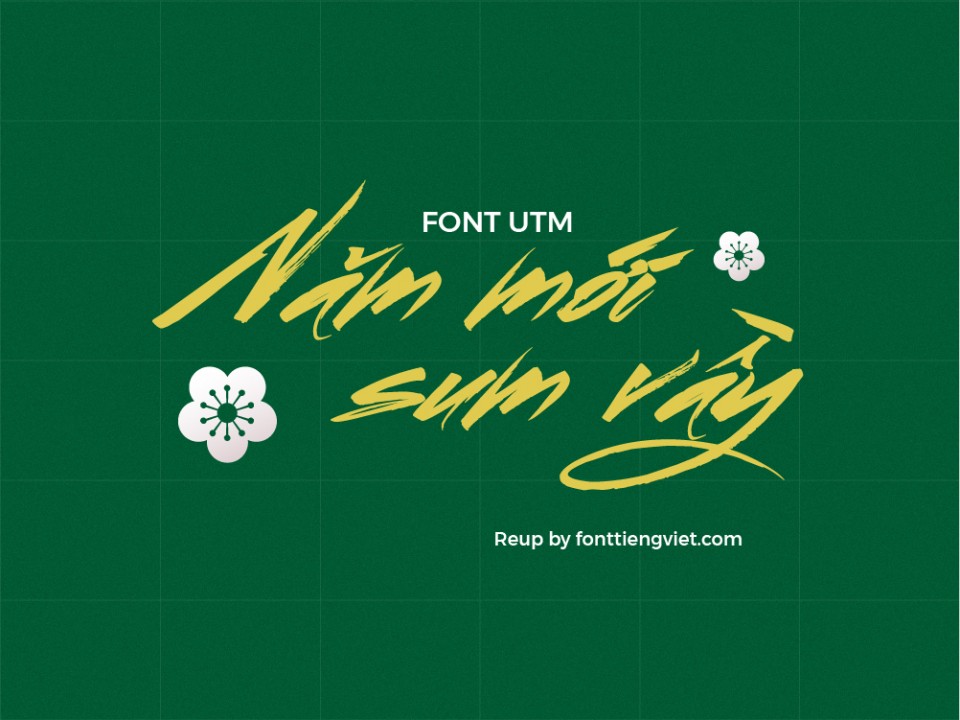
Giới thiệu về Font việt hóa UTM Ông Đồ Trẻ – Tết
Trong không khí rộn ràng của những ngày cuối năm, việc tìm kiếm một bộ Font Chữ mang đậm bản sắc văn hóa dân tộc là điều vô cùng cần thiết. Font việt hóa UTM Ông Đồ Trẻ – Tết chính là lựa chọn hoàn hảo để thổi hồn vào các thiết kế chúc mừng năm mới. Được phát triển dựa trên phong cách thư pháp hiện đại, bộ font này không chỉ giữ được nét mềm mại, uyển chuyển của bút nghiên mà còn mang hơi thở trẻ trung, năng động. Đây là công cụ đắc lực giúp các bạn học sinh và thầy cô dễ dàng tạo ra những tấm thiệp, biểu ngữ hay báo tường đầy ấn tượng cho dịp Tết nguyên đán sắp tới.
Đặc điểm nổi bật của bộ font thư pháp hiện đại
Thiết kế tối ưu cho tiếng Việt
Điểm mạnh nhất của Font việt hóa UTM Ông Đồ Trẻ – Tết là khả năng hiển thị tiếng Việt hoàn hảo, không bị lỗi dấu hay sai lệch khoảng cách. Từng nét chữ được chăm chút tỉ mỉ, mô phỏng lại cách đưa bút của những ông đồ thời nay, vừa phóng khoáng lại vừa dễ đọc. Điều này giúp nội dung truyền tải trở nên gần gũi và trang trọng hơn trong mắt người xem.
Ứng dụng đa dạng trong học đường và đời sống
Bộ font này cực kỳ phù hợp cho các dự án thiết kế banner sự kiện trường học, trang trí bao lì xì hoặc làm tiêu đề cho các bài thuyết trình về chủ đề văn hóa dân gian. Sự linh hoạt giữa nét thanh và nét đậm tạo nên sự cân bằng thị giác tuyệt vời, giúp các tác phẩm đồ họa trở nên chuyên nghiệp hơn bao giờ hết mà không tốn quá nhiều công sức chỉnh sửa thủ công.
Kết luận và cách sử dụng hiệu quả
Việc sở hữu Font việt hóa UTM Ông Đồ Trẻ – Tết sẽ giúp bạn tự tin sáng tạo nên những sản phẩm mang đậm phong vị Tết Việt. Để đạt hiệu quả thẩm mỹ cao nhất, bạn nên kết hợp font chữ này với các tông màu truyền thống như đỏ, vàng hoặc xanh lá cây. Hãy bắt đầu trải nghiệm ngay bộ Font Miễn Phí, Font Việt Hóa, Font việt hóa UTM Ông Đồ Trẻ – Tết để mang lại không gian rực rỡ và ý nghĩa cho những tác phẩm thiết kế của mình trong mùa xuân này.